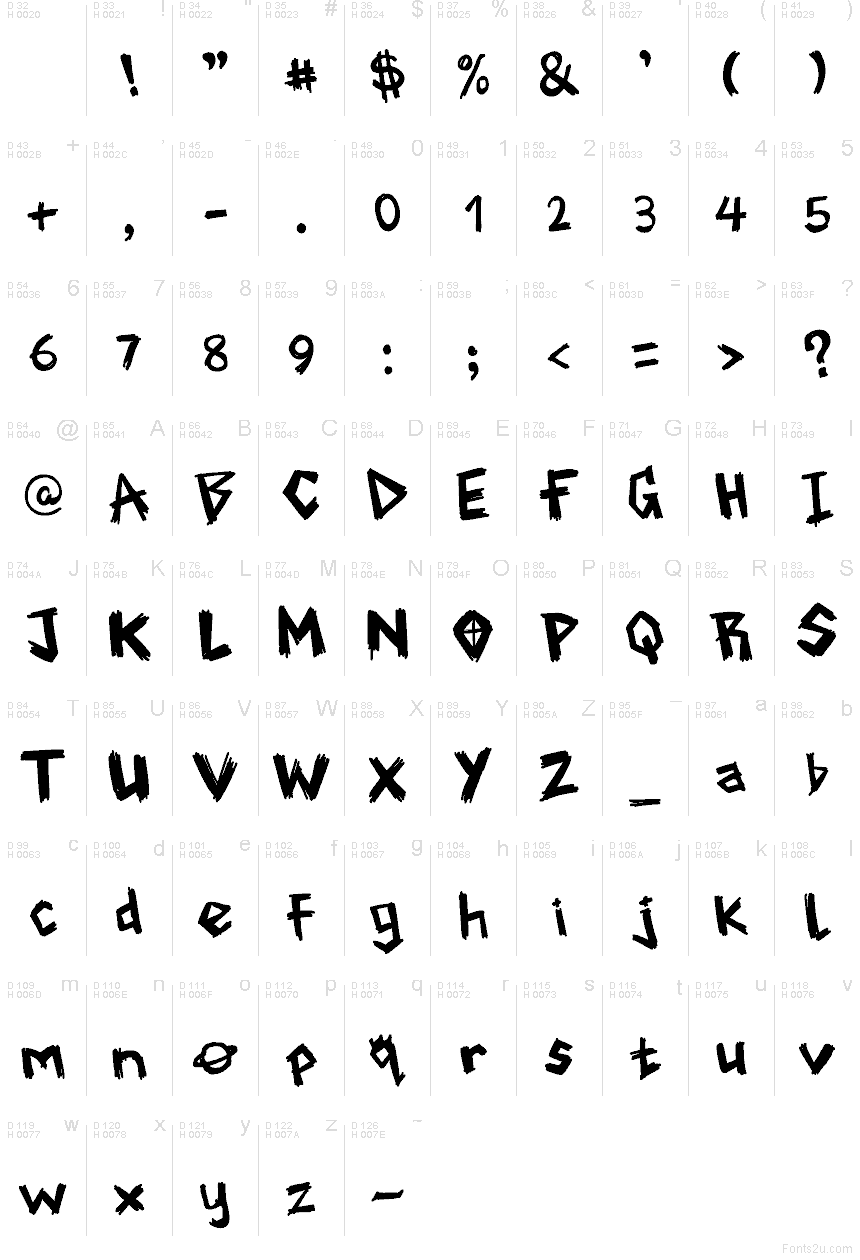
Unruly by dayo
Unruly od Dayo je bezplatné písmo štýlu „trash“ s drsnými ťahmi štetca, zubatými okrajmi a uvoľneným, ručne kresleným rytmom, ktorý dodáva každému znaku ošúchaný a nepokojný vzhľad. Formy sa nepravidelne nakláňajú a lámu, takže celý dizajn pôsobí skôr ako unáhlené pouličné písmo než ako uhladená typografia.
Unruly funguje výborne v titulkoch plagátov, hudobnej grafike, zinoch, brandingu inšpirovanom graffiti alebo pri odvážnej grafike na sociálne siete, pretože jej poškriabaná textúra prenáša surovú, improvizovanú energiu do krátkych nápisov. Skvele pasuje aj na návrhy nálepiek, potlače oblečenia a letáky na akcie, keď chcete, aby písmo pôsobilo skôr spontánne než vyšperkovane.